Top 20 font chữ cho du lịch, homestay, resort và travel agency
Gợi ý 20 font TH Việt hóa cho thiết kế du lịch, homestay, resort, travel agency, brochure tour và social media.
Thiết kế du lịch cần font tạo được cảm giác muốn xách ba lô lên đường, nhưng vẫn phải đọc rõ trên brochure, bảng giá, lịch trình tour, landing page và bài social. Một font đẹp cho resort chưa chắc hợp travel agency, và một font retro cho homestay phố cổ cũng không nên dùng cho app đặt tour hiện đại.
Bài viết này gợi ý 20 font TH Việt hóa phù hợp cho du lịch, homestay, resort, travel agency và brochure tour. Mỗi font đều có link tải và ảnh preview để bạn test nhanh với tên địa điểm, tên tour hoặc concept thương hiệu thật.
Cách chọn font cho thiết kế du lịch, homestay và resort
Với homestay và city tour, font nên gợi được tinh thần địa phương: cổ điển, gần gũi, có chút thủ công hoặc hoài niệm. Với resort cao cấp, font cần thanh lịch, thoáng và không quá nhiều chi tiết. Với travel agency, độ đọc và tính hệ thống quan trọng hơn: font phải dùng tốt cho lịch trình, giá tour, điều kiện đặt chỗ và CTA.
Một công thức dễ dùng là chọn một font display cho headline, một font sans-serif rõ ràng cho thông tin tour, và một font viết tay hoặc script cho chi tiết cảm xúc. Không nên dùng cả bài bằng font trang trí, vì khách cần đọc nhanh ngày khởi hànhg, giá, điểm đến và chính sách.
Top 20 font TH Việt hóa cho du lịch, homestay, resort và travel agency
1. TH Busan Garden
TH Busan Garden phù hợp với tour Hàn Quốc, homestay phong cách Hàn, poster check-in và bộ nhận diện có hơi thở trẻ trung. Khi dùng cho thiết kế du lịch, hãy đặt font ở tiêu đề tour, tên địa điểm, poster check-in, bìa brochure hoặc headline social. Với phần lịch trình, giá, hotline và điều kiện đặt phòng, nên phối cùng font phụ dễ đọc hơn.
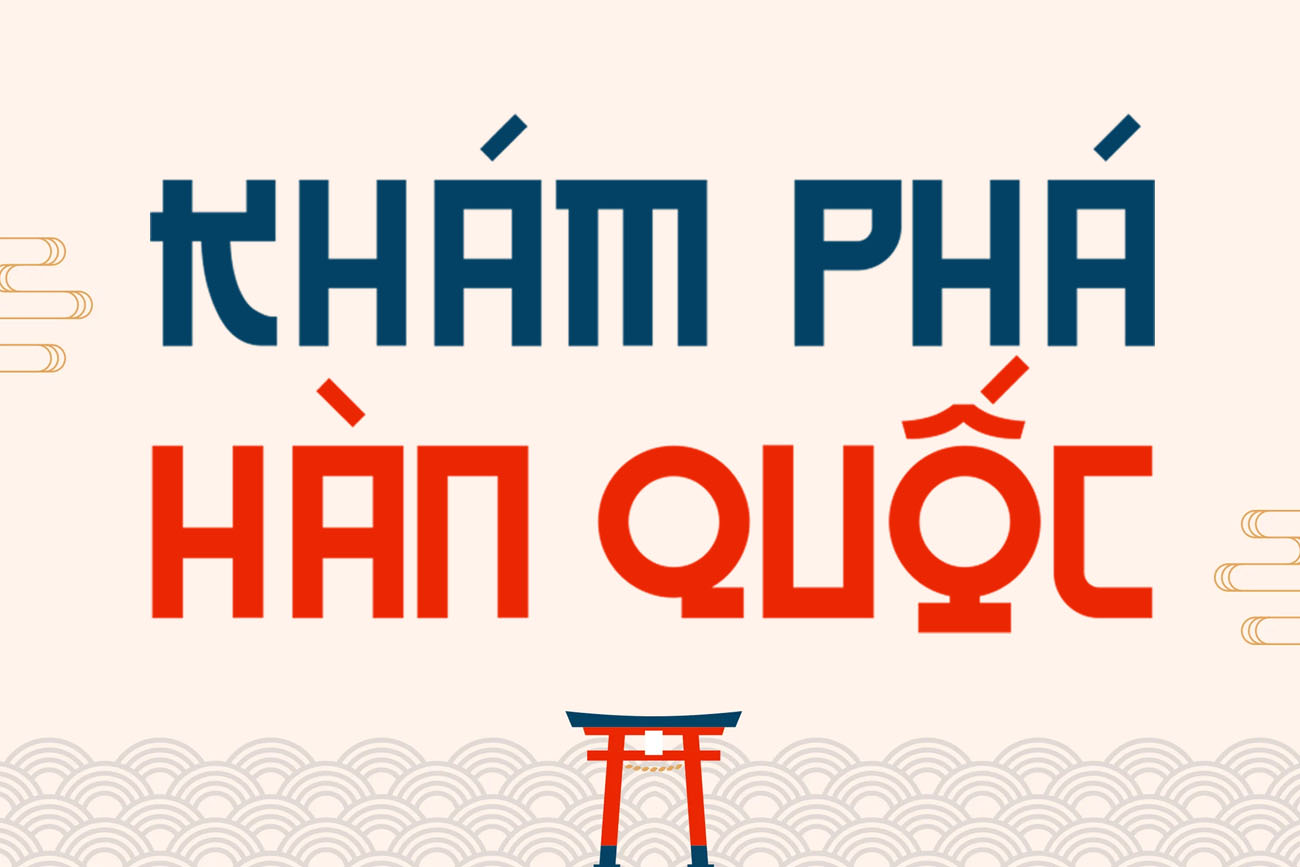
2. TH Joypor
TH Joypor phù hợp với tour Hàn, cafe homestay, travel content mùa đông và bài social cần cảm giác vui nhưng vẫn rõ chữ. Khi dùng cho thiết kế du lịch, hãy đặt font ở tiêu đề tour, tên địa điểm, poster check-in, bìa brochure hoặc headline social. Với phần lịch trình, giá, hotline và điều kiện đặt phòng, nên phối cùng font phụ dễ đọc hơn.
3. TH AKAMI
TH AKAMI phù hợp với tour Nhật Bản, ryokan, sushi trip, poster trải nghiệm văn hóa và brochure hành trình Á Đông. Khi dùng cho thiết kế du lịch, hãy đặt font ở tiêu đề tour, tên địa điểm, poster check-in, bìa brochure hoặc headline social. Với phần lịch trình, giá, hotline và điều kiện đặt phòng, nên phối cùng font phụ dễ đọc hơn.
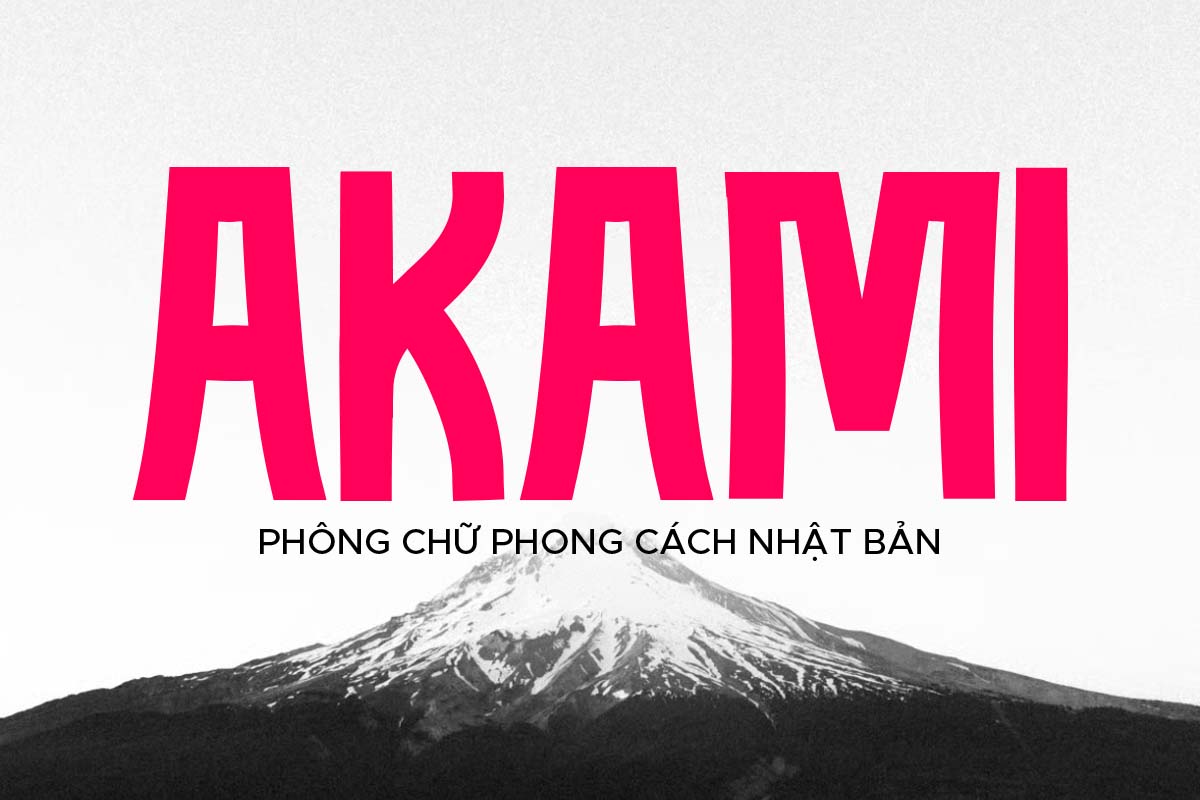
4. TH Gareda
TH Gareda phù hợp với du lịch Nhật, resort phong cách zen, tour lễ hội và ấn phẩm có chất văn hóa rõ. Khi dùng cho thiết kế du lịch, hãy đặt font ở tiêu đề tour, tên địa điểm, poster check-in, bìa brochure hoặc headline social. Với phần lịch trình, giá, hotline và điều kiện đặt phòng, nên phối cùng font phụ dễ đọc hơn.
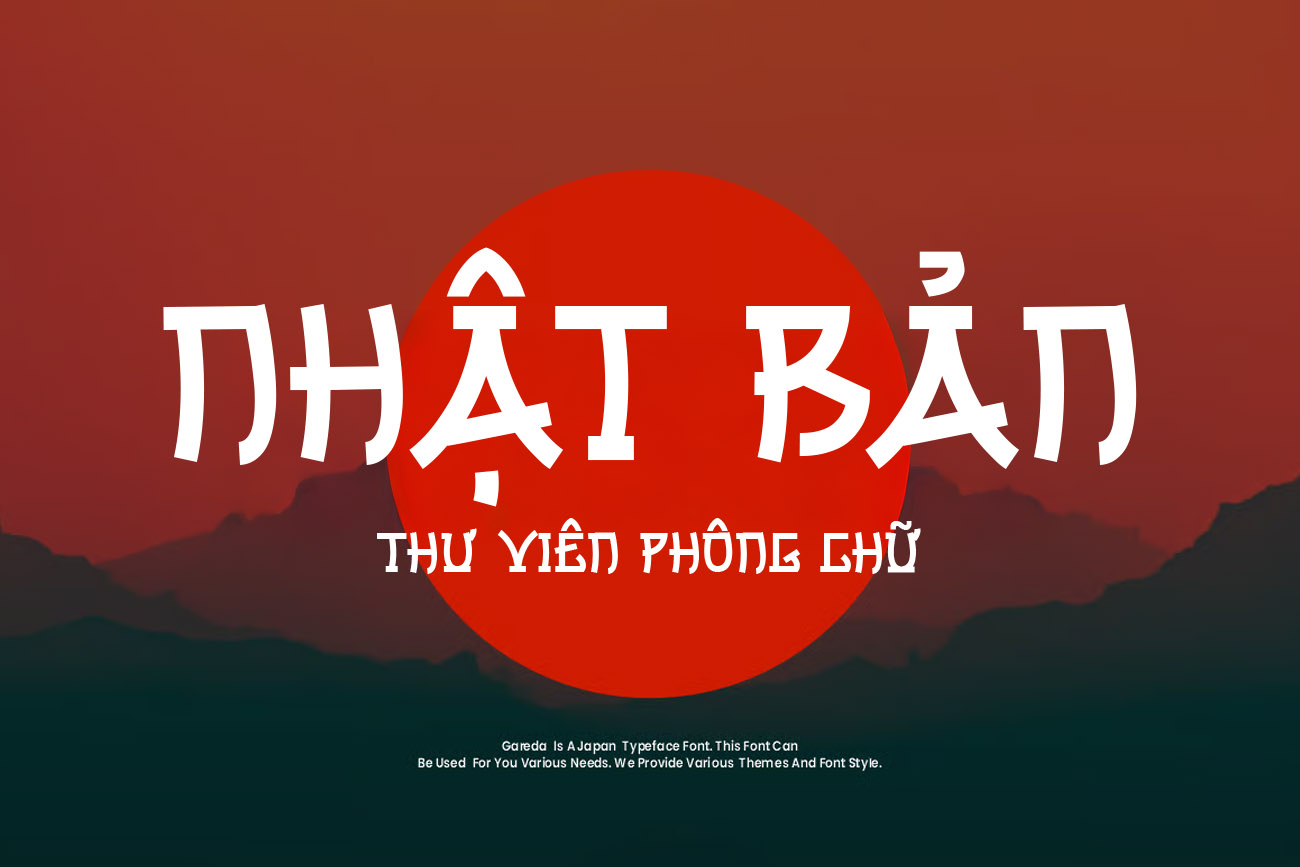
5. TH Juzho Kaizen
TH Juzho Kaizen phù hợp với brochure tour Nhật, workshop văn hóa, trải nghiệm trà đạo và các thiết kế cần tinh thần thủ công. Khi dùng cho thiết kế du lịch, hãy đặt font ở tiêu đề tour, tên địa điểm, poster check-in, bìa brochure hoặc headline social. Với phần lịch trình, giá, hotline và điều kiện đặt phòng, nên phối cùng font phụ dễ đọc hơn.
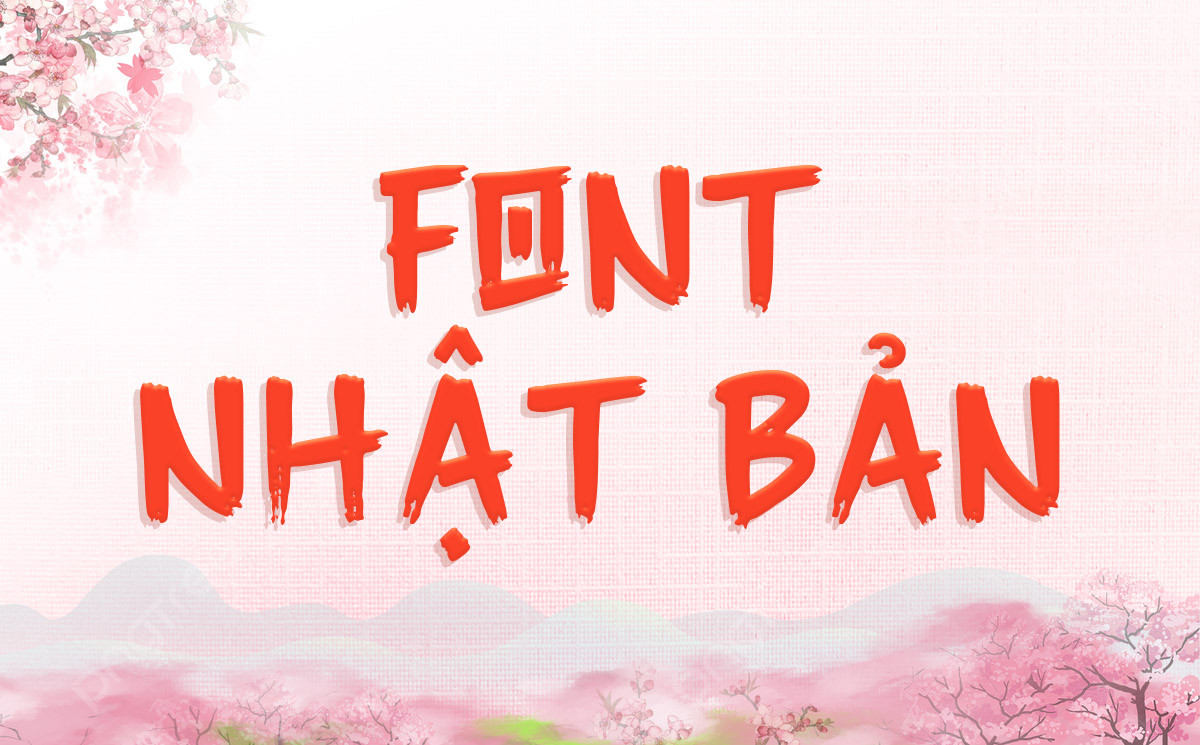
6. TH Nhatban 2
TH Nhatban 2 phù hợp với poster du lịch Nhật, ẩm thực Nhật, homestay theo chủ đề và key visual mùa hoa anh đào. Khi dùng cho thiết kế du lịch, hãy đặt font ở tiêu đề tour, tên địa điểm, poster check-in, bìa brochure hoặc headline social. Với phần lịch trình, giá, hotline và điều kiện đặt phòng, nên phối cùng font phụ dễ đọc hơn.
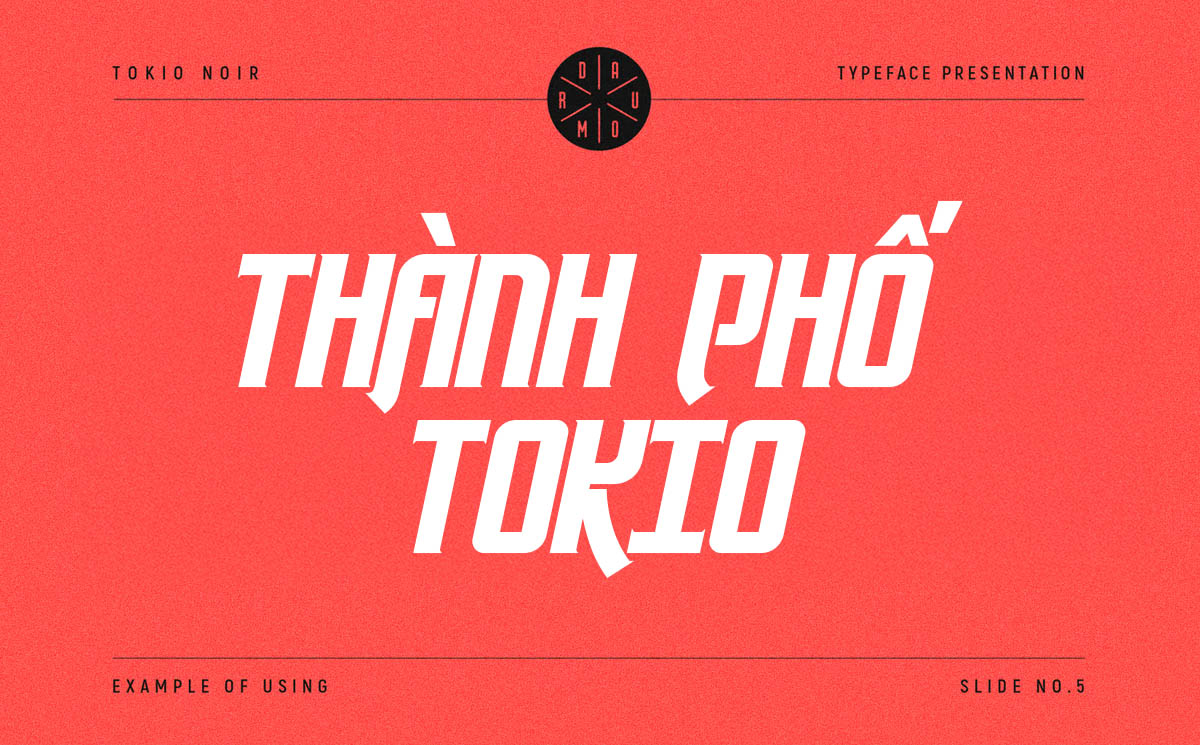
7. TH Colombo Sans
TH Colombo Sans phù hợp với tour phố cổ, city tour, brochure Hà Nội, Đà Lạt, Hội An và các concept hoài niệm. Khi dùng cho thiết kế du lịch, hãy đặt font ở tiêu đề tour, tên địa điểm, poster check-in, bìa brochure hoặc headline social. Với phần lịch trình, giá, hotline và điều kiện đặt phòng, nên phối cùng font phụ dễ đọc hơn.
8. TH Hoaico 20
TH Hoaico 20 phù hợp với tour Sài Gòn xưa, homestay vintage, quán cafe du lịch và bảng hiệu có cảm giác địa phương. Khi dùng cho thiết kế du lịch, hãy đặt font ở tiêu đề tour, tên địa điểm, poster check-in, bìa brochure hoặc headline social. Với phần lịch trình, giá, hotline và điều kiện đặt phòng, nên phối cùng font phụ dễ đọc hơn.
9. TH Roge
TH Roge phù hợp với poster tour retro, travel postcard, workshop ảnh phim và các campaign mùa hè giàu màu sắc. Khi dùng cho thiết kế du lịch, hãy đặt font ở tiêu đề tour, tên địa điểm, poster check-in, bìa brochure hoặc headline social. Với phần lịch trình, giá, hotline và điều kiện đặt phòng, nên phối cùng font phụ dễ đọc hơn.
Travel agency và chiến dịch digital
Với agency bán tour, app đặt vé hoặc chiến dịch social, TH Legacy Sans, TH Algance, TH Seona Display và TH Giabe giúp bố cục hiện đại hơn. Các font chủ đề như TH Busan Garden, TH AKAMI hoặc TH Gareda nên dùng theo từng tuyến tour cụ thể để tạo điểm nhận diện.
Font du lịch tốt không chỉ đẹp mà còn giúp khách hiểu nhanh chuyến đi: đi đâu, khi nào, giá bao nhiêu và trải nghiệm có gì đặc biệt. Hãy chọn font theo mô hình kinh doanh, test trên brochure, poster và mobile social trước khi dùng đồng bộ cho cả thương hiệu.